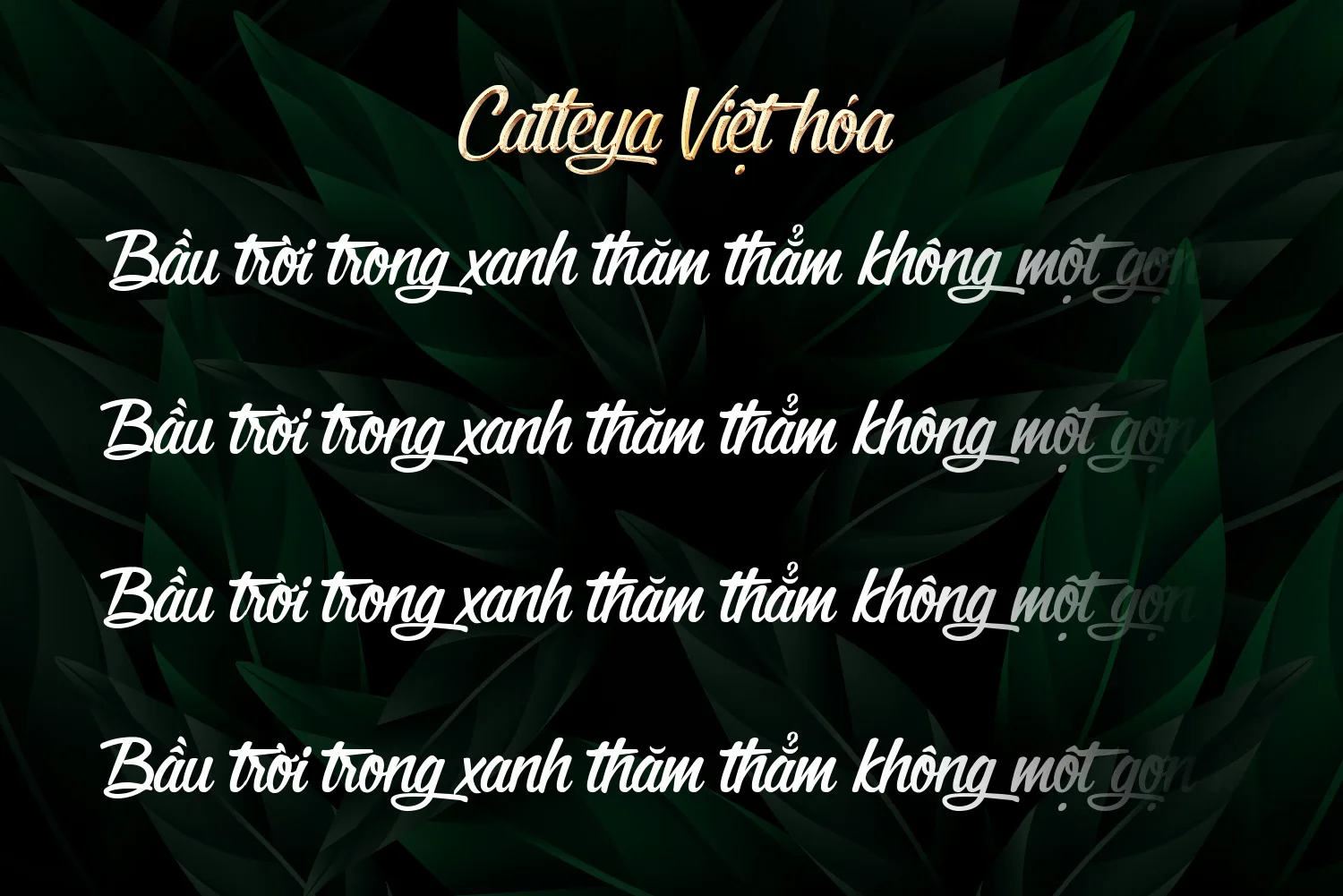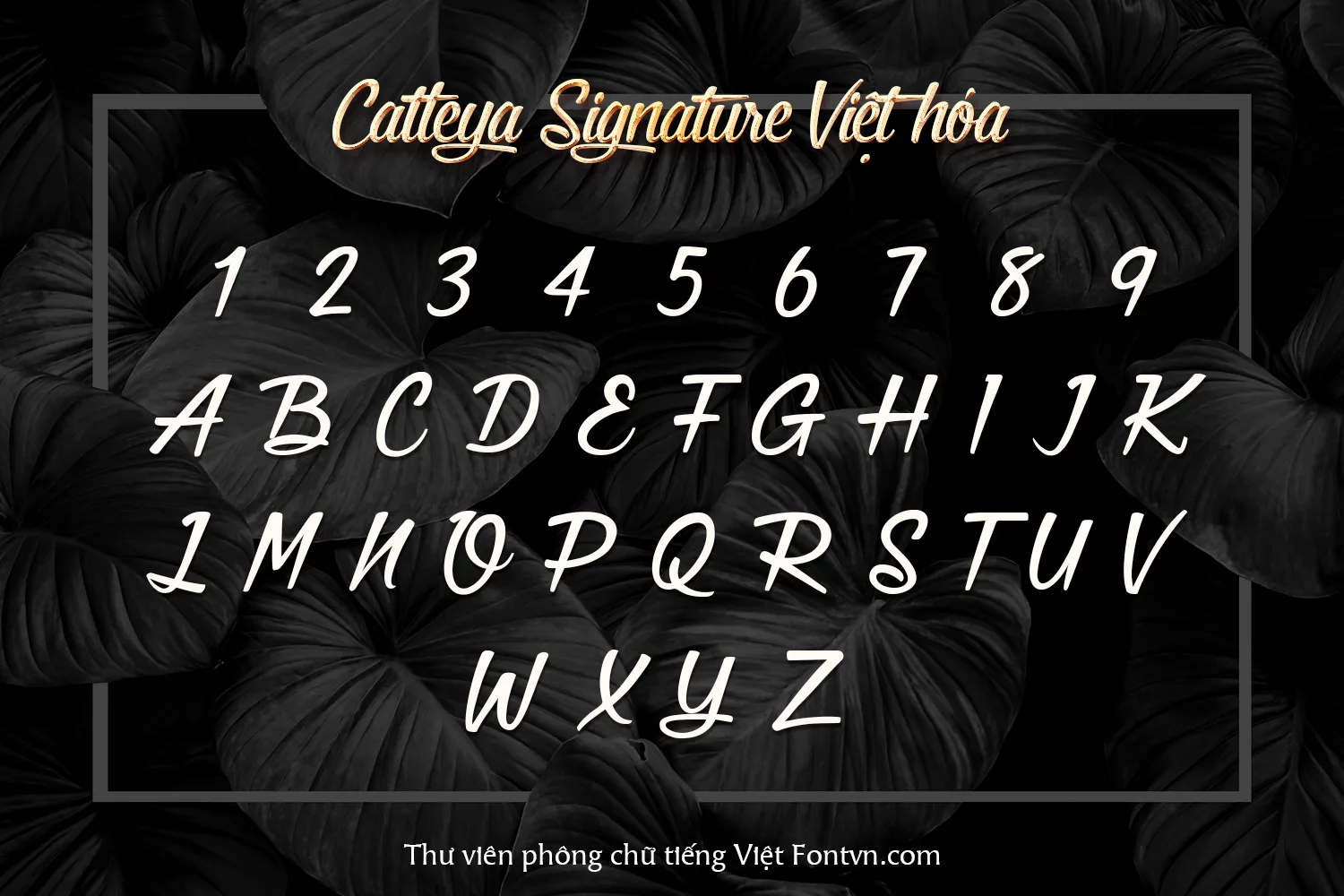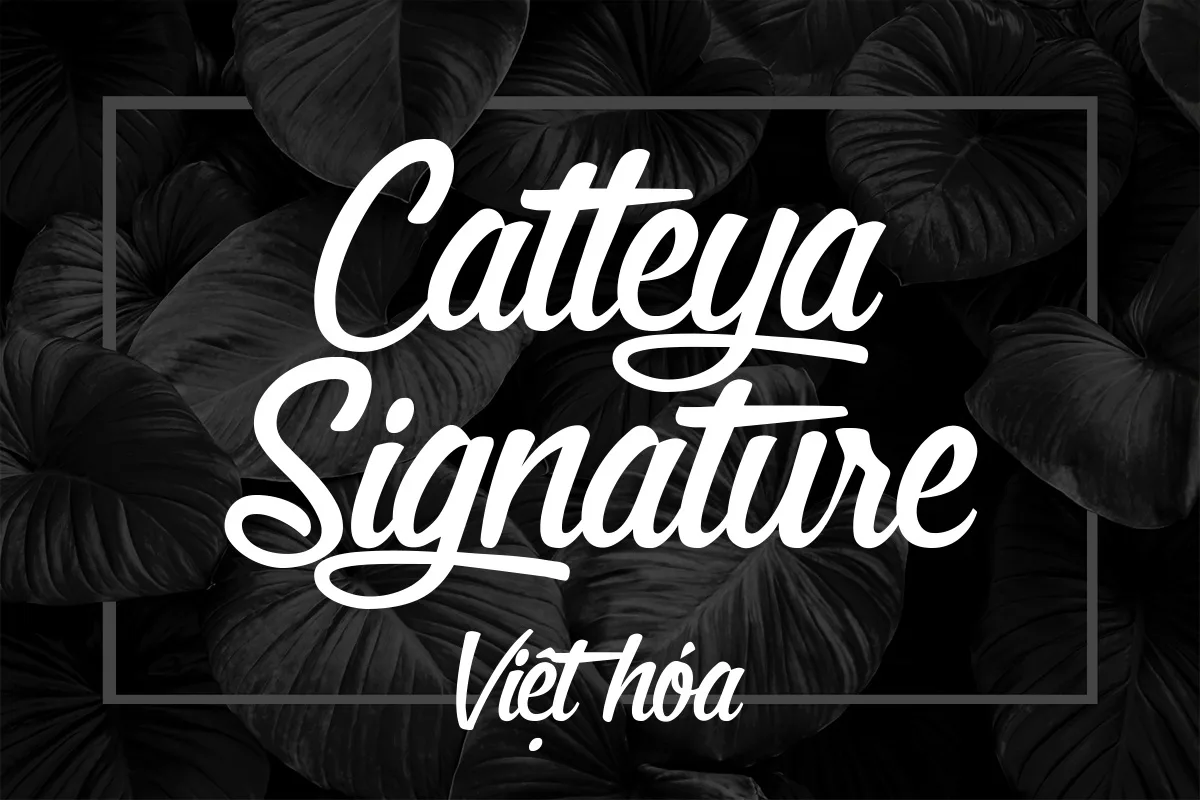
DVN – Catleya Signature Việt hóa: Font chữ ký tay sang trọng và tinh tế
Catleya Signature là một font chữ script mang phong cách chữ ký hiện đại, mềm mại và uyển chuyển. Các nét chữ được thiết kế liền mạch, mang hơi hướng handwritten calligraphy, giúp văn bản trông tự nhiên và tinh tế như chữ viết tay thực thụ.
Điểm nổi bật của font này là:
• Nét bút lượn sóng mượt mà: phù hợp cho thiết kế mang tính cá nhân, thương hiệu cá nhân hoặc những sản phẩm cần sự tinh tế.
• Chữ hoa có dáng thanh thoát, nhấn nhá mạnh: tạo ấn tượng ngay từ cái nhìn đầu tiên.
• Chữ thường gọn gàng, dễ kết hợp: giữ sự cân bằng, giúp văn bản vừa trang trọng vừa gần gũi.
• Bao gồm đầy đủ bộ ký tự chữ cái, dấu câu và glyph mở rộng (196 glyphs), hỗ trợ thiết kế đa dạng.
Ứng dụng:
Font DVN – Catleya Signature Việt hóa đặc biệt phù hợp cho:
• Logo thương hiệu, bao bì sản phẩm.
• Thiệp mời, chữ ký số, watermark.
• Các thiết kế sáng tạo trong lĩnh vực thời trang, mỹ phẩm, phong cách sống.
👉 Đây là lựa chọn lý tưởng nếu bạn đang tìm một font sang trọng nhưng vẫn mang nét tự nhiên và cá tính.